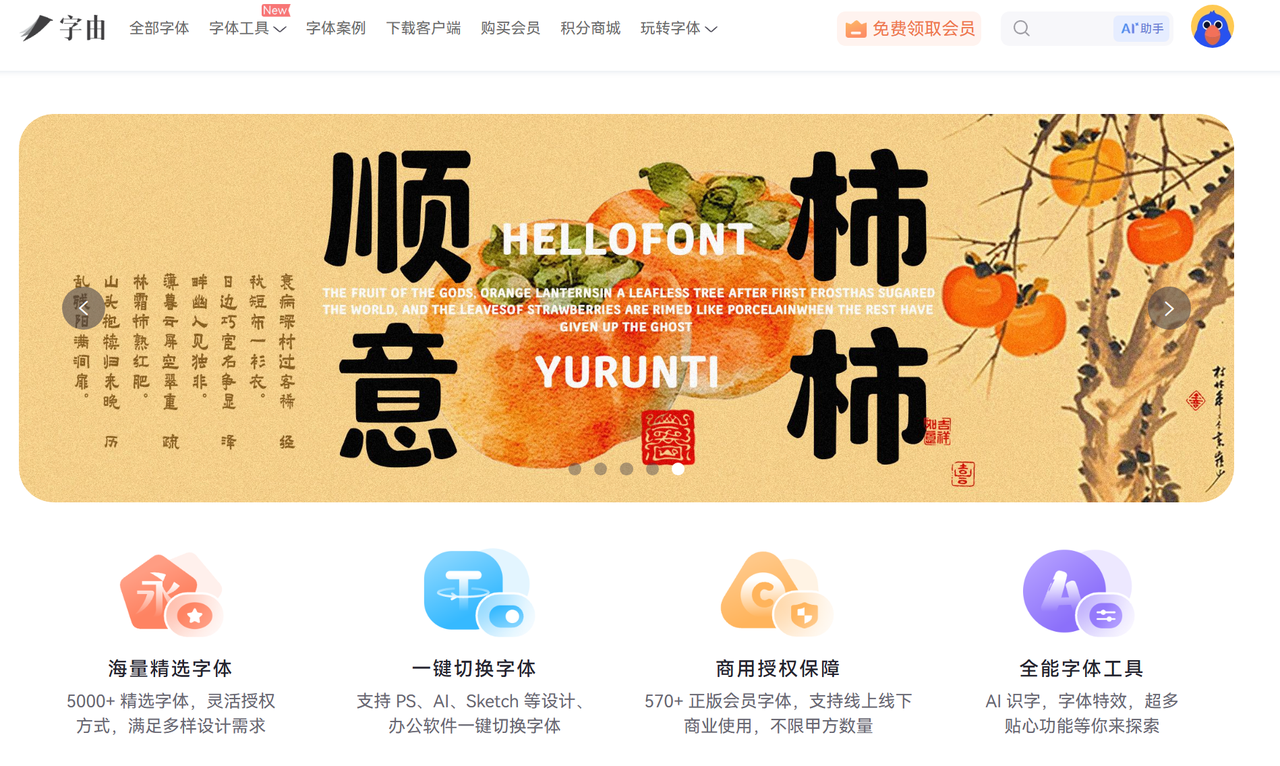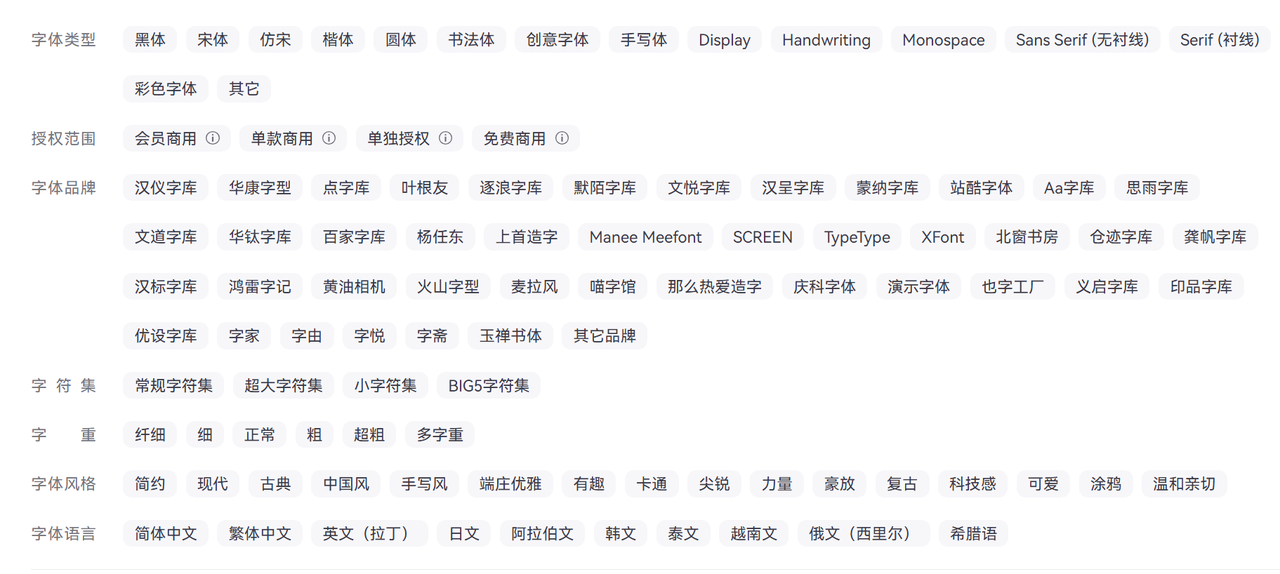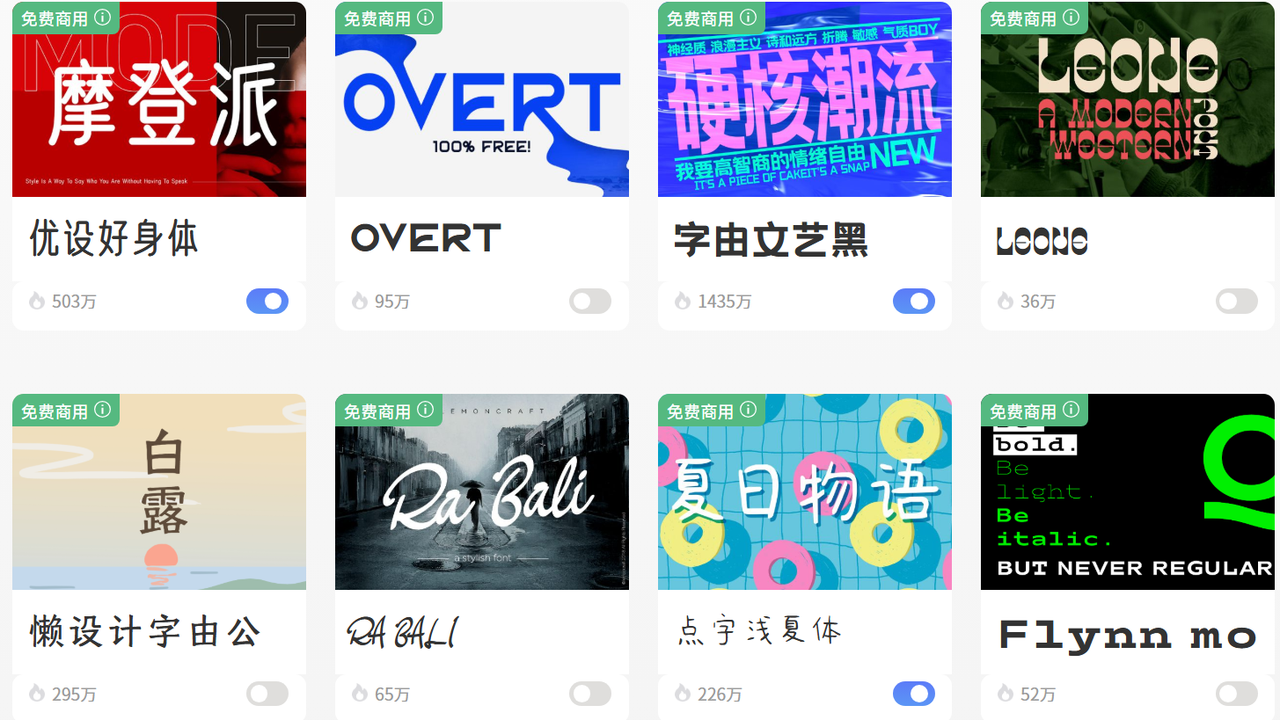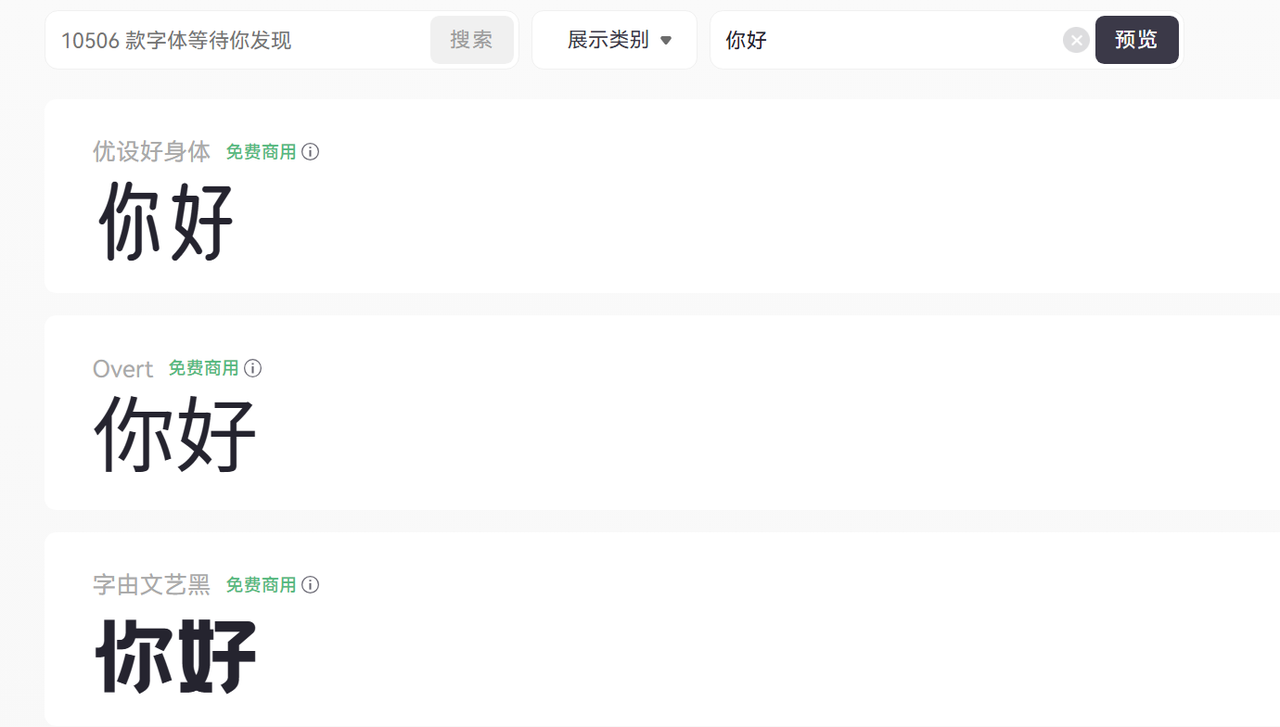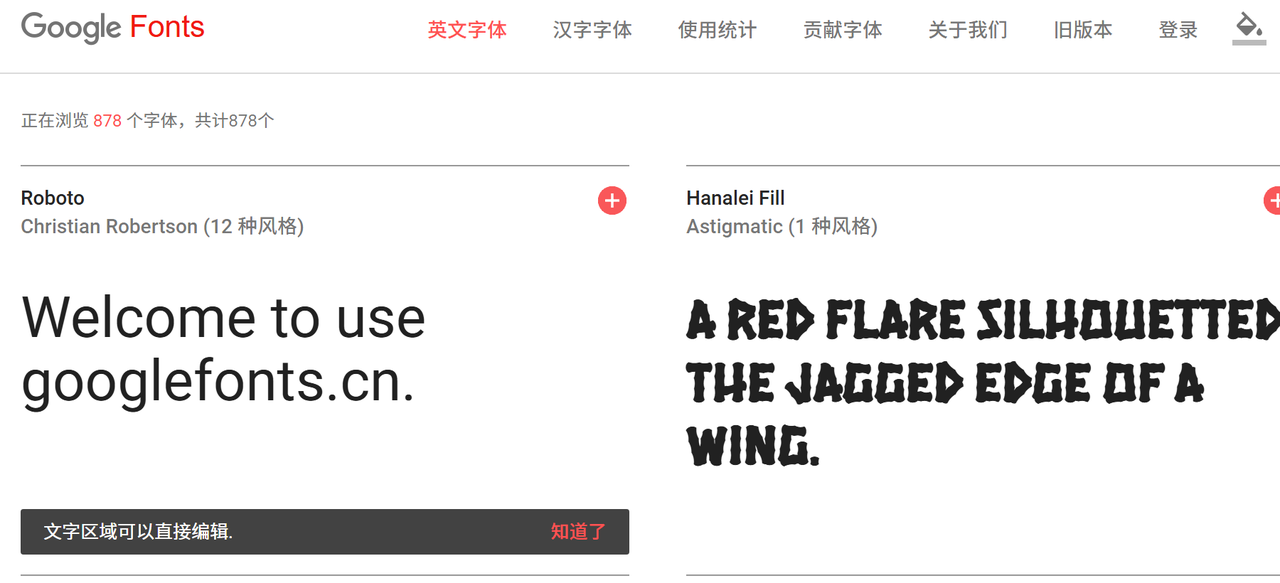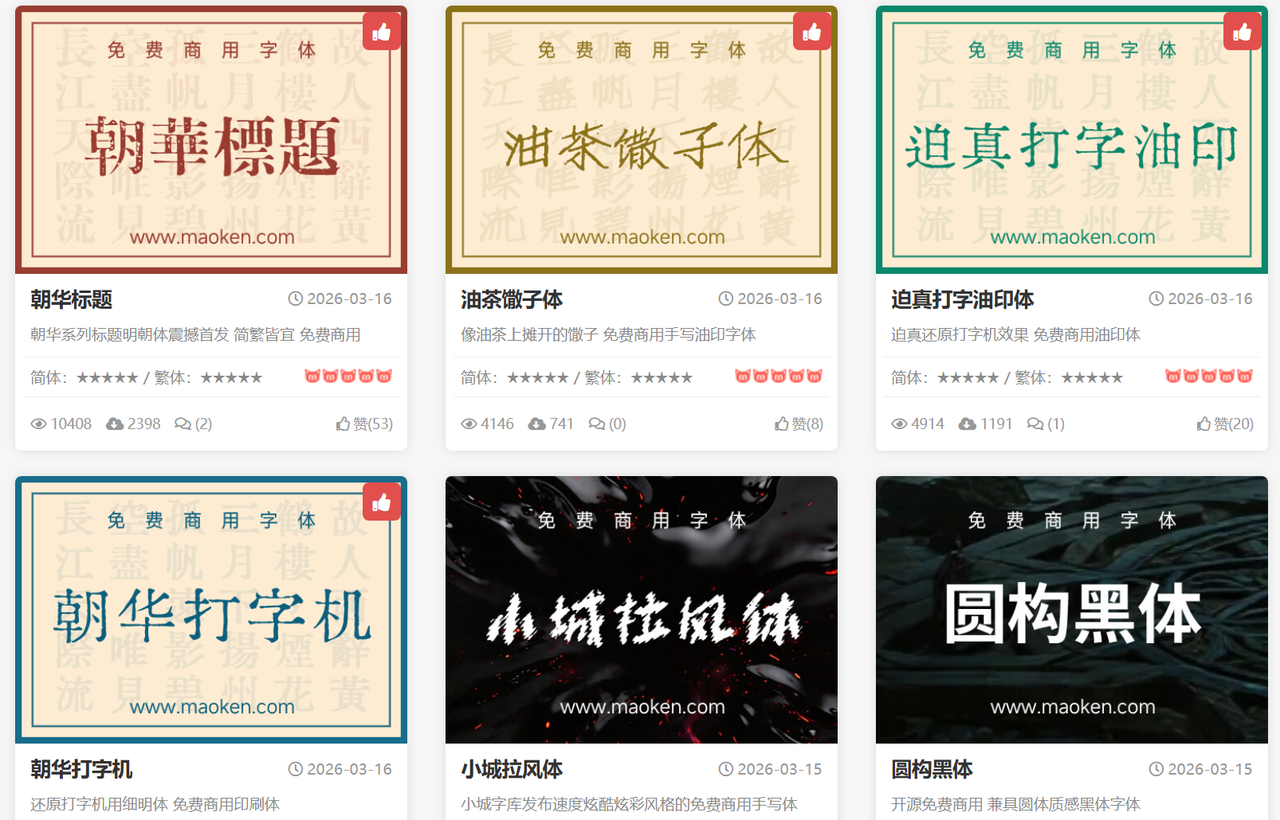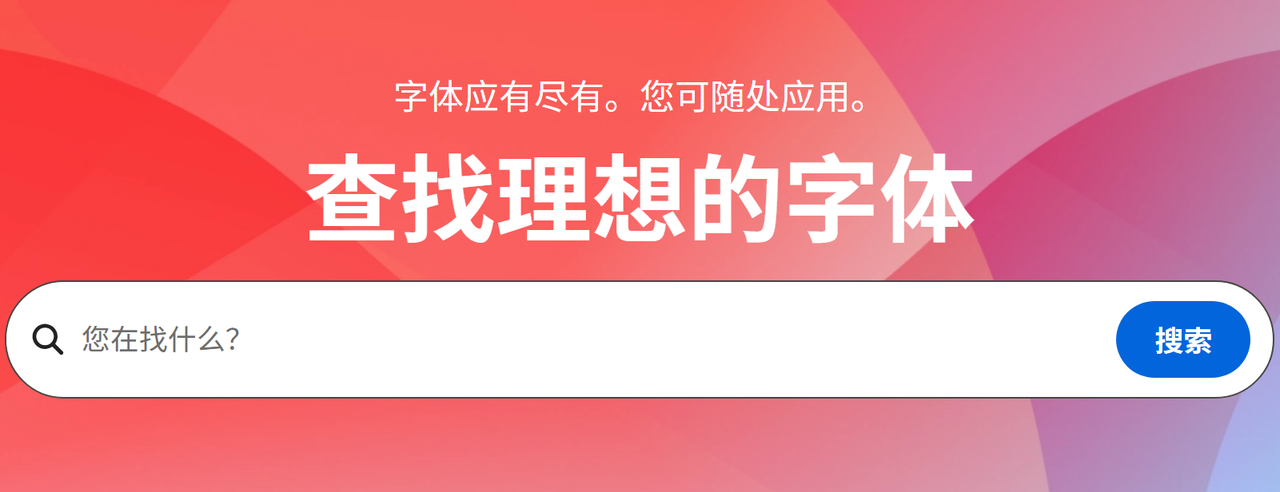
免费字体包下载合集|2026商用字体包推荐,设计师亲测可用
打开PS,空白画布对着你,脑子里已经有了排版方案——偏偏就卡在一个字体上。搜了半小时,要么是付费墙,要么下载下来发现根本不能商用,要么压缩包里藏着一堆广告软件。这种感觉,做过设计的人都懂。2026年了,字体资源其实已经足够丰富,缺的只是一个靠谱的整理。这篇文章不是简单的网址罗列,而是我实际用过、踩过坑之后筛出来的清单。每个平台的适用场景、下载方式、注意事项都会说清楚。
一、字由网——2026最值得下载的免费字体包平台
如果你只能收藏这篇文章里的一个字体平台,那就选字由。字由是目前国内免费字体包资源最丰富、使用体验最好的字体管理平台之一。它不只是一个"字体下载网站",更像是一个字体操作系统——装上客户端之后,你可以直接在PS、AI、Sketch、Figma等设计软件里一键激活免费字体包,根本不需要手动下载、安装、重启软件这套繁琐流程。
① 免费字体包数量庞大,分类清晰 字由目前收录超过10000款字体,其中有相当数量可直接免费使用,涵盖中文黑体、宋体、书法体、手写体,以及英文衬线、无衬线、装饰字体。你可以按风格(简约/可爱/现代/复古)、按品牌快速筛选出最合适的字体包,极大节省选字时间。
② 设有专属免费字体包专区,授权透明 字由专门设有"免费商用字体包"专区,每款字体都标注了授权范围(个人免费、商用免费、需授权)。你不需要自己去翻授权协议,平台已经帮你筛选好了。在一个版权意识越来越强的时代,能找到一个授权清晰的免费字体包下载平台,本身就是最大的省心。
③ 在线预览,下载前就能看效果 字由支持在线输入文字实时预览字体效果,不用把整个字体包下载下来,就能看到自己的标题换上某款字体是什么感觉,选字效率翻倍。
字由平台精选免费字体包推荐:
字体名称 风格 适用场景
站酷系列免费字体包 活泼、现代 电商、海报、标题
庞门正道粗书宋 复古、有力量 品牌、国潮设计
优设标题黑 硬朗、科技感 Banner、大标题
思源黑体免费字体包 简洁、专业 UI、正文、报告
阿里巴巴普惠体 中性、大方 商业通用场景
二、Google Fonts——英文字体的天花板,全部免费商用
做英文排版、出海项目、APP界面,Google Fonts是绕不开的存在。1500+款字体,全部免费,全部可商用,托管在Google服务器,网页直接调用也不用担心授权问题。下载方式也很直接,选好字体点"Download family"就能拿到TTF文件。
三、猫啃网——专门收录免费可商用中文字体
猫啃网干了一件很有价值的事:专门收录那些明确授权免费商用的中文字体,并且会持续追踪授权状态,一旦某款字体改了授权协议,站长会及时更新标注。网站收录的字体不算多,但每款都经过人工核实,宁缺毋滥。如果你在做有商业变现的项目——不管是电商详情页、品牌物料还是短视频封面——在这里找字体是比较稳妥的选择。
四、Adobe Fonts
如果你有Adobe Creative Cloud订阅,Adobe Fonts里超过20,000款字体都可以直接使用,在PS、AI里一键同步激活,且商用授权随订阅自动覆盖。虽然不是"免费"资源,但对于已有CC订阅的设计师来说,这绝对是被低估的巨大福利。
字体这件事,入门门槛低,但上限很高。用对一款字体,可以让平平无奇的排版瞬间升级;用错一款字体,再好的构图都显得廉价。更重要的是,在版权日益规范的今天,"免费好用还能商用"的字体资源,其实并不稀缺——只是很多人还没找到对的渠道。无论你是学生党、自由设计师、运营从业者,还是刚起步的品牌主理人,上面这份清单都能满足日常95%以上的字体需求。收藏好,下次选字的时候不用再满网络乱翻了。